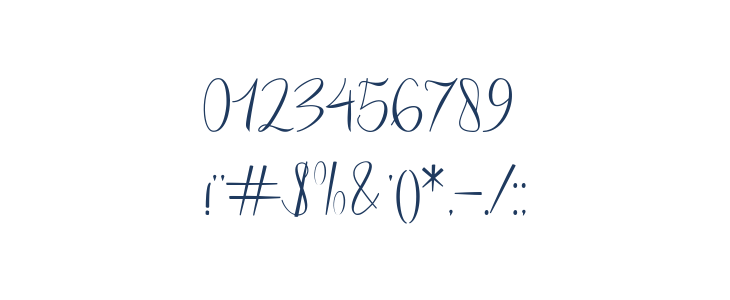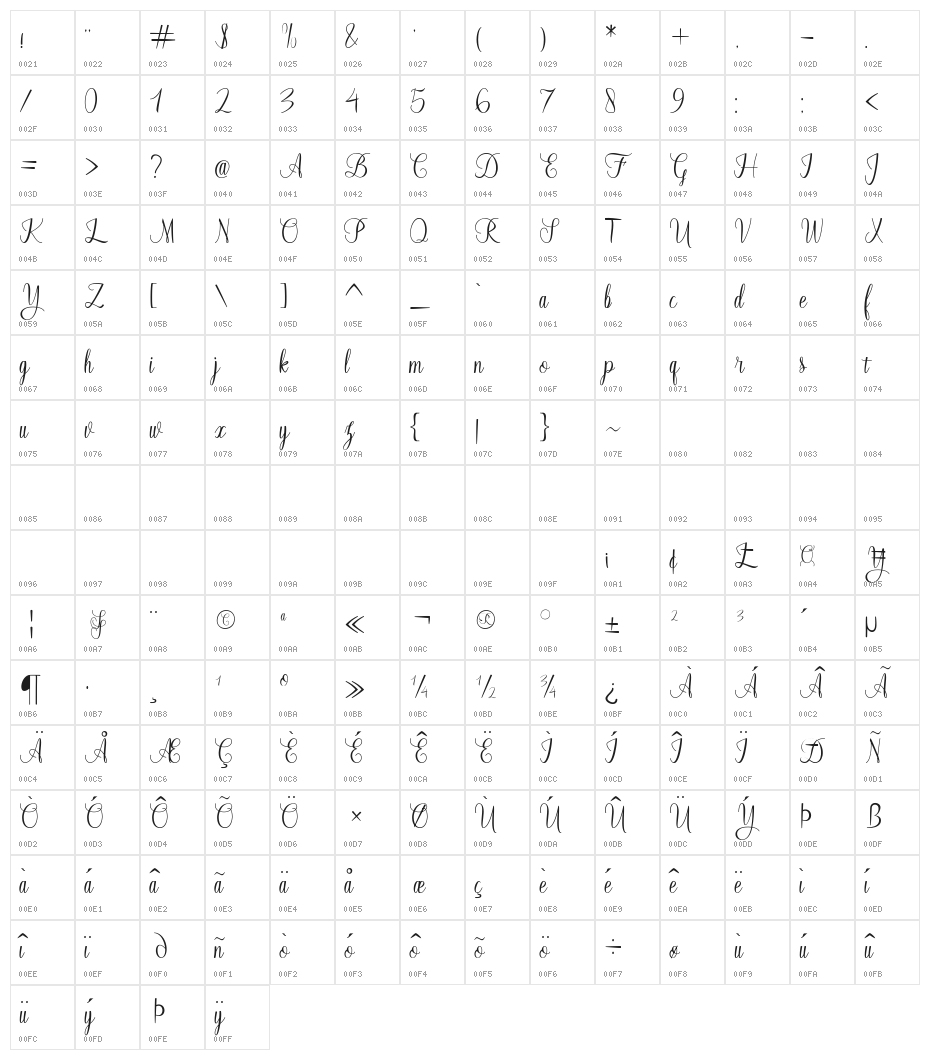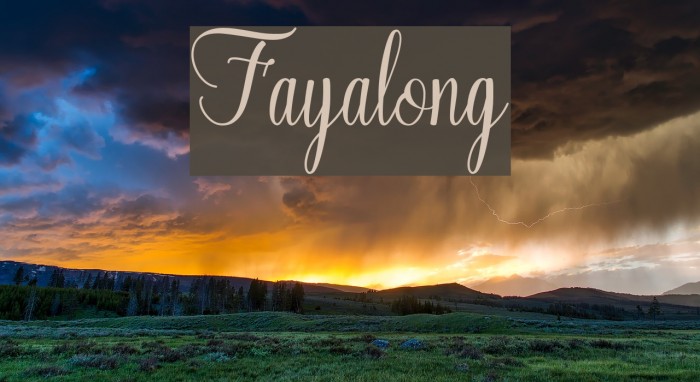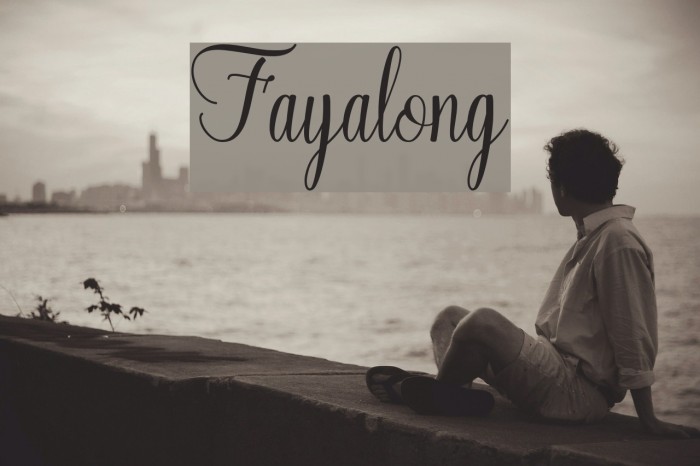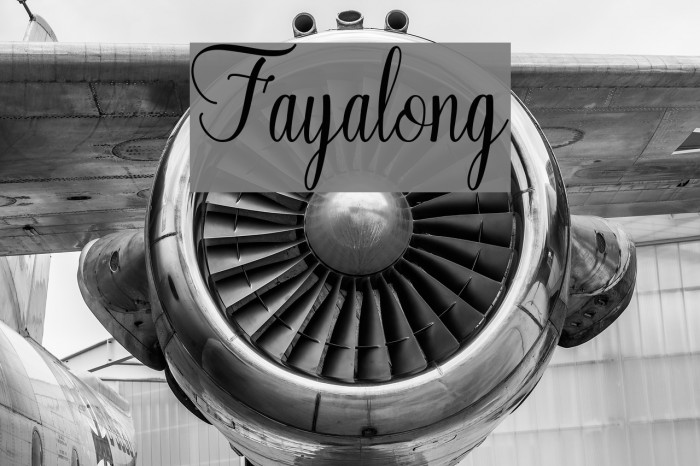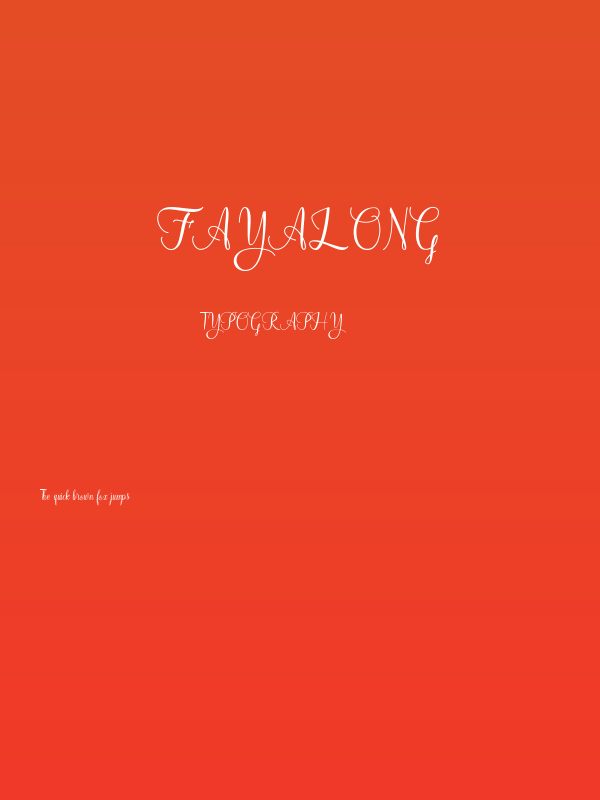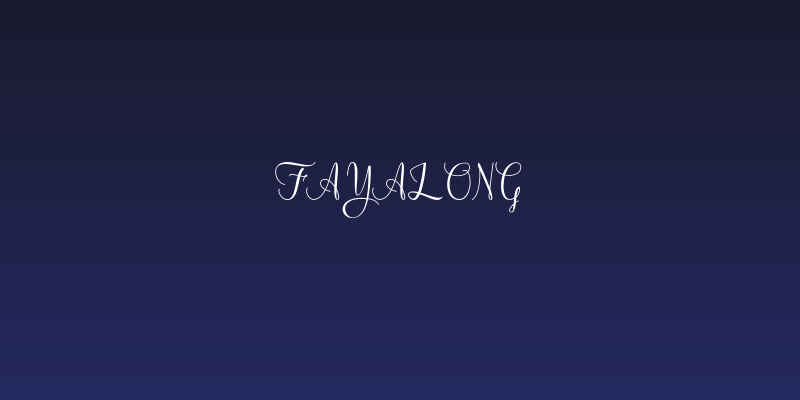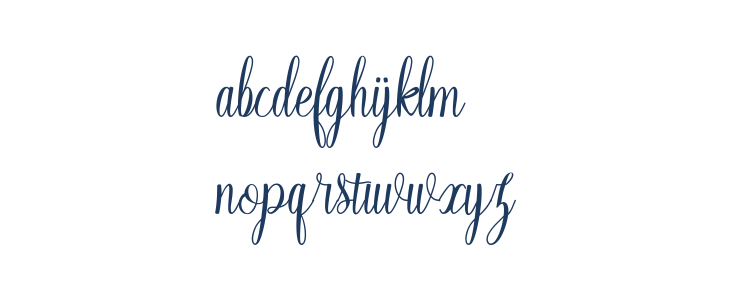
Fayalong Font
✎ Script
| Kategorien | Script |
| Gesamtstil | Elegant, Sophisticated |
| Anwendungsfall | Logos, Invitations, Branding |
| Vorgeschlagene Projekte | Ideal for wedding invitations, elegant branding, high-end product packaging, and sophisticated event posters. |